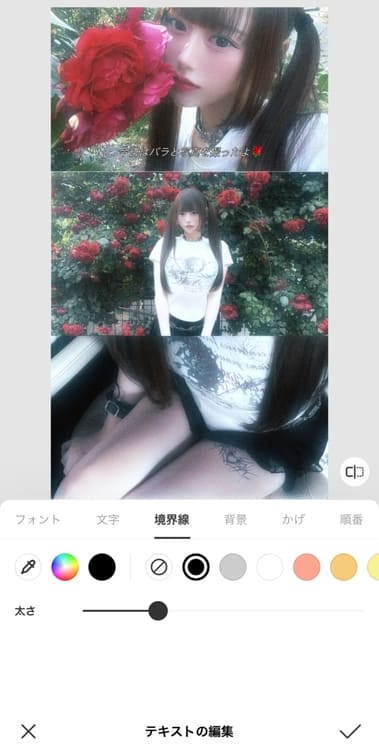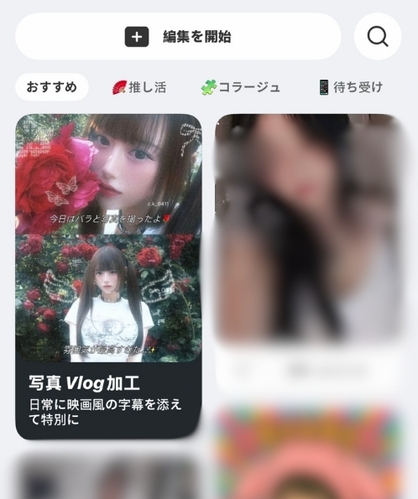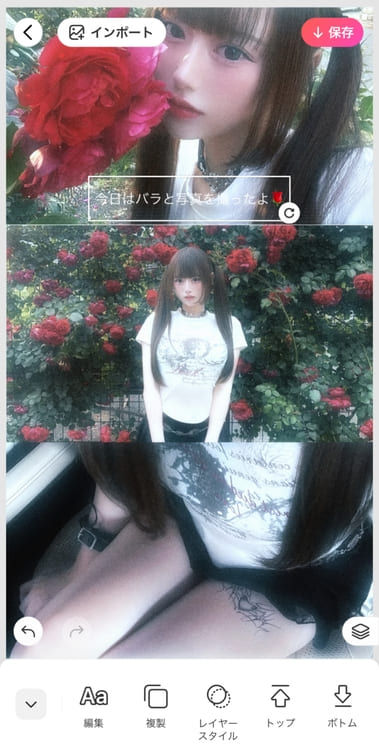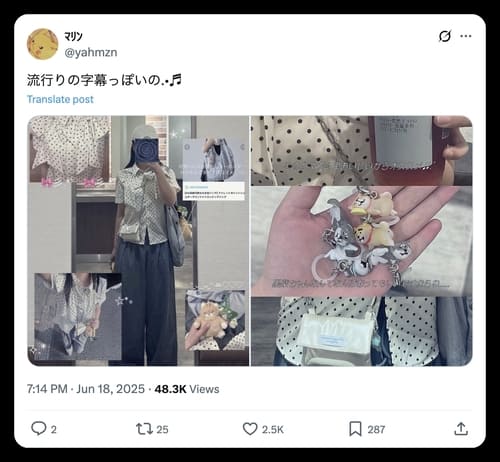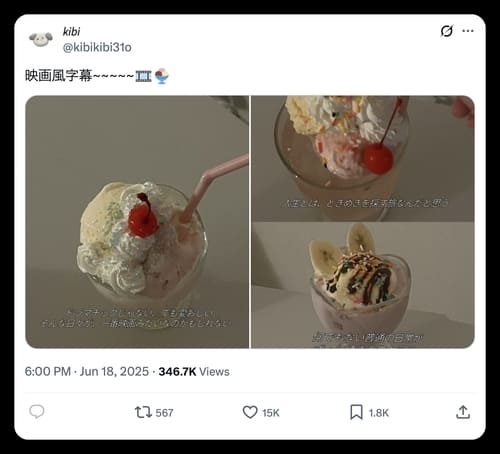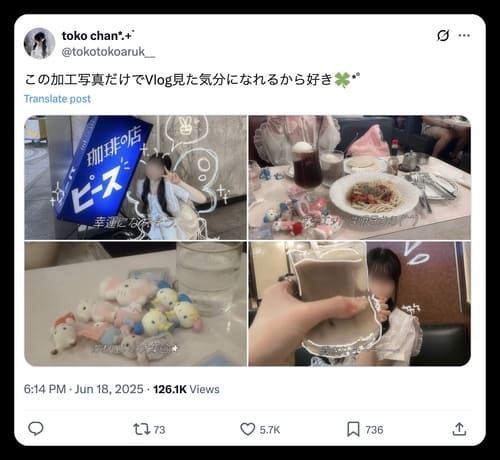
映画字幕フォントで写真に文字を入れる!人気の文字入れアプリ&加工法【2026年最新・無料】
ねぇねぇ、最近SNSでよく見る、あの可愛くておしゃれな写真知ってる?そう、まるで映画のワンシーンみたいな「vlog風・映画字幕フォント加工」!
この記事では、大人気のこの加工方法を、みんな大好き「BeautyPlus」を使って分かりやすく解説!まるで映画の主人公になったみたいに、あなたの写真もキラキラ輝かせちゃおう!🚀💖
SNSで話題沸騰中!写真に文字を入れる『映画字幕フォント風』の写真加工が大人気
最近韓国女子やZ世代、アイドルからトレンドが始まり、SNSでバズっているのが、『vlog風写真』と呼ばれる写真加工スタイル。写真に映画の字幕のようなフォントでテキストを入れて、3枚の画像を縦に並べたレイアウトが特徴です。なんとも言えないエモくさと、まるでVlogの1カットみたいに“動画を静止したような雰囲気”が絶妙で、その瞬間の気持ちまで閉じ込められる感じが人気です。
映画字幕フォントの加工ポイント
Vlog風写真加工 - 人気
• 写真に映画字幕のようなフォントを入れる
映画字幕風のフォントで「その時の気持ち」や「一言メモ」を入れることで、ただの風景や日常スナップが、“誰かの記憶”や“ドラマの一場面”に変わり、エモさがアップ。
• 全体に白っぽいフィルターで統一感を出す
白っぽいフィルターによって、懐かしさや温かさが写真全体ににじみ出ます。特別な演出をしなくても、“あの頃の空気感”や“過ぎ去った時間の尊さ”を感じさせてくれるような効果が得られます。
• 縦長3枚のコラージュで、Vlog動画のスクショ風にする
3枚の縦長写真をコラージュすることで、時間の流れや連続性が生まれます。これは、vlog動画でよくある「朝 → 昼 → 夜」や「視線の移動」などを1枚の画像で再現するような感覚です。日常の一場面を3枚で切り取るだけで、「一日をドキュメント化」するような感覚を味わえます。加工しながら“自分の人生を映像で見ている”ような、不思議な自己投影感が得られることも!
このVlog風・映画字幕フォント加工は、シンプルな構成ながら、構図・文字・トーンが整って見えるため、「映える写真」「センスのある投稿」になるのもこの加工の大きなメリットです。「なんか雰囲気ある」「vlogっぽくてかわいい」と注目度100%!
「EPIK」でバズり中のVlog風テンプレート
このVlog・映画字幕風フォントのコラージュ加工が一気に広まったきっかけは、実は「EPIK」という写真加工アプリがきっかけです。XやInstagramなどのSNSで「旅行写真」「風景」「日常のスナップ」「カフェ飯」「友達との記念写真」などを、この写真に文字を入れるスタイルで投稿する人が続出しています!統一感のあるフィルターと、映画のような字幕風のフォントでまとめることで日常を映画のワンシーンみたいに見せることができるのが、たくさんの人を魅了しているようです。
BeautyPlusでも映画字幕風の文字入れ加工が可能!
画像編集アプリ「BeautyPlus」は、文字入れアプリとしても人気です。もちろん、この映画の字幕風フォントを活用したvlog風加工も簡単に楽しめちゃいます。 使い方はとてもシンプルで、初心者でも迷わずおしゃれに仕上げることができます。
Vlog風・写真に文字を入れる方法
Vlogスタイルのテンプレートを選択する
1. アプリのホームの右上から「vlog」「映画風の字幕」を検索
2. 好きなテンプレートを選ぶ
3. 好きな写真を3枚アップロードするだけ!
BeautyPlusアプリには、Vlog風のテンプレートを選んで3枚の写真をアップするだけで、統一感のある映画字幕風フォントコラージュ加工が自動で作れちゃいます。映画のワンシーンのような雰囲気を出せるヴィンテージ系や淡いトーンのフィルターが充実していて、自分だけのオリジナルな写真も作成可能!さらに、字幕風のフォントも選べるので、文字の配置やデザインにこだわりたい人にもぴったりです!
DIY派におすすめ!自分だけの映画字幕風コラージュを作ろう
テンプレートに頼らず、もっと自由に写真に文字を入れたい方には、こちらの方法がおすすめ!
オリジナル写真コラージュの手順
1. ホームから「コラージュ」→ 好きなレイアウトを選択 → 写真をアップロード
2. 保存後、「編集」をタップ
1. (オプション)「編集」→「調整」→「ヴィンテージ」でレトロ加工や粒子感を追加
1. 「フィルター」から好きなフィルターを適用
難しい操作は、一切必要なく簡単にVlog風の世界感を演出してくれます。
BeautyPlusアプリを使うとこんなメリットも!
• 簡単なのに自由に作れる: わかりやすい画面だから、初めてでも迷わず編集できます。
• 字幕っぽい文字も思い通りに入れられる!映画の字幕みたいなフォントも使えるし、文字の太さ・色・向きなども細かく調整できます。
• 美肌加工や明るさ調整もできる!文字を入れるだけじゃなく、肌や明るさも一緒にキレイにできるのが嬉しいポイント。
映画風字幕フォントの入れ方
• テキストを追加 → 「Martian Light」フォントを選ぶ
• 斜体 + 黒の縁取りを設定 → 配置を調整して完成
複数の画像を1枚に写真を縦や横にコラージュするのもOK。1枚で画像に文字入れしてインスタストーリーとして投稿するのもよし!自由度を求めるならDIYがベストです!
フィルターを追加
Vlogスタイルの編集のおすすめ機能
• C35やC39:ミルキー系、白みがかったヴィンテージ調が◎また、肌の色や背景がふんわり白くなり、清潔感と透明感がアップし、写真にも透明感をプラスできちゃいます。
• MD1やMD2:モダン風でレトロ感をUP。クールで洗練された印象を与えながらちょっと大人っぽい、静かなvlog風世界観が作れます。
• DaydreamやSurreal:ふわふわで光の色合いが抜群。光がにじむような柔らかい色合いで、夢の中のような幻想的な雰囲気に、日常の写真でも、キラキラした思い出感が演出できちゃいます。
貼れるスタンプを追加
ドットアート・トキメキジェム・3Dスウィートランド・リボン系など写真の雰囲気に合ったスタンプをポイントで入れてみてください。テーマやシーンに合わせたスタンプを選ぶことで、写真にストーリーや世界観を加えることができ、無地背景の写真やシンプルな構図でも、華やかさや可愛さをプラスできます。
おすすめ映画風字幕フォント
Martian Lightyや細めのサンセリフ体が字幕風で人気!映画やvlogの字幕のような印象を作れるため、写真にストーリー性が生まれます。また細くて洗練されたフォントなので、どんな写真にもなじみやすく、おしゃれさがアップ。あえて控えめなフォントを使うことで、写真の空気感や感情が引き立ちます。
テンプレを使った後でも、オリジナルに画像編集できるので、是非自分だけの思いの詰まった1枚を作成してみてください。
おすすめの撮影シーン
最後に、「どんな写真にこのVlog風・映画字幕風フォント加工が合うの?」という方のために、シーン別のおすすめをご紹介します。 字幕フォントと淡いフィルターが、あなたの思い出を“映画のワンシーン”のように変えてくれます。
1. 旅行写真
その土地の風景や食べ物を字幕風に記録。旅先での何気ない風景や出会いを1枚の写真に残してみてください。
2. 友達との思い出
フィルターをかけて、レトロな記念写真に。笑いすぎて涙が出たあの日、駅のホームで話し込んだ夜、なんてことない帰り道。そんな日常の写真にフィルターをかけて、字幕でひとこと添えると、あの日の“音”や“気配”まで思い出せるように。
3. 日常のPlog
コーヒーや空の写真も、思いの文字を添えるだけで物語風に。お気に入りのカフェで飲んだラテ、ベランダで見た夕暮れ、何気なく撮った足元の影。そんな「ふつう」の日も、字幕風の文字を添えることで、かけがえのない一日だったと気づけちゃいます。
Vlog風の加工は、ただの写真を「記録」から「物語」に変えてくれる魔法のような手法です。その時の光、空気、気持ちまで閉じ込めてくれるから、見返すたびに胸がぎゅっとなる――そんな写真がきっと残せます。
あなたの「好き」や「大切」を、字幕と一緒に残してみませんか?